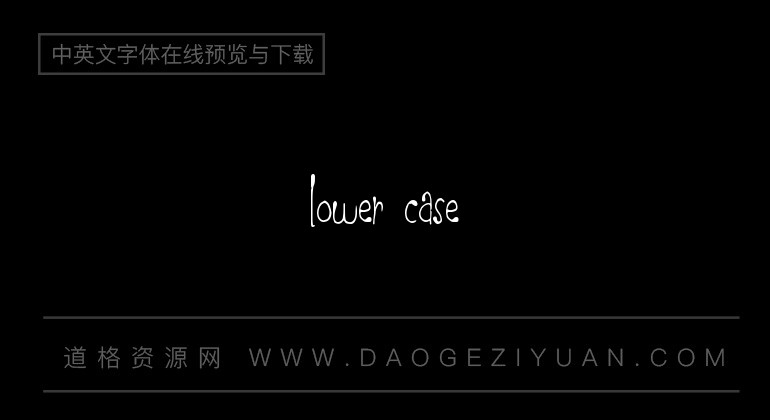
Lower Case
Lower Case 字体是一种字体设计风格,它的特点是将所有的字母都设计成小写形式。与之相对应的是 Upper Case 字体,即所有字母都是大写形式。 Lower Case 字体设计风格最早出现在古希腊时期,随着时间的推移,这种设计风格逐渐成为了书法和印刷中常用的字体风格之一。现代英语书写和排版中,大多数情况下都使用 Lower Case 字体。 相比于 Upper Case 字体,Lower Case 字体更加柔和自然,更符合我们阅读时的习惯和认知。此外,Lower Case 字母之间的间距更加平衡,使得字体更加美观。在设计师中,Lower Case 字体也被广泛使用,特别是在品牌设计和标志设计上,使用 Lower Case 字体可以营造出亲切、轻松的感觉,更加符合现代人的审美需求。
Lower Case是一款非常不错的手写艺术字体,具有很好的视觉感,适合于文化类的宣传设计、商业类品牌的广告和产品包装设计以及个性化文字排版等较多场景。